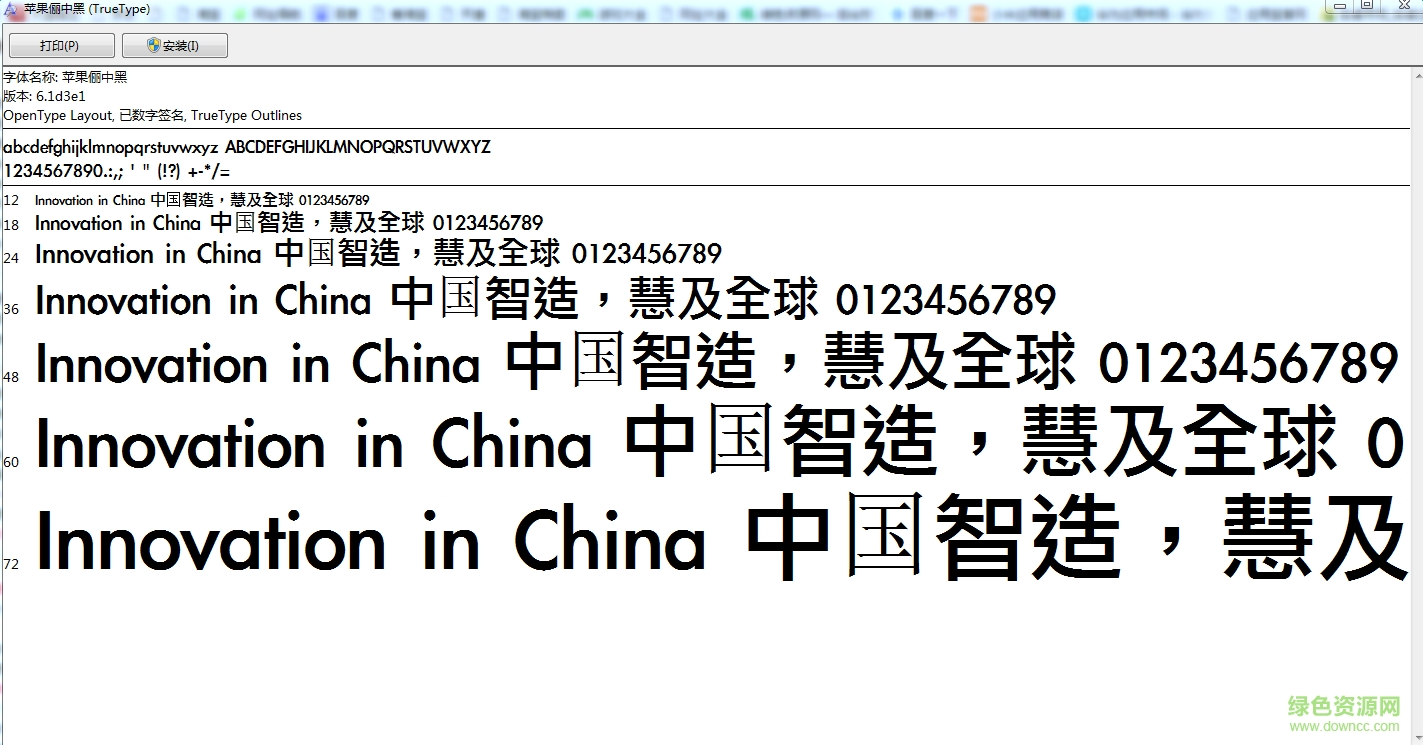
蘋果儷中黑字體是一款端正大方的黑體字體,字形簡潔清晰,十分好看,常用于廣告、印刷、包裝等領(lǐng)域,歡迎有需要者來綠色資源網(wǎng)下載!
蘋果麗黑字體,是仿蘋果操作系統(tǒng)的一款字體,初用時(shí)感覺可能會(huì)不習(xí)慣,大多數(shù)用在游戲,廣告中效果比較好。